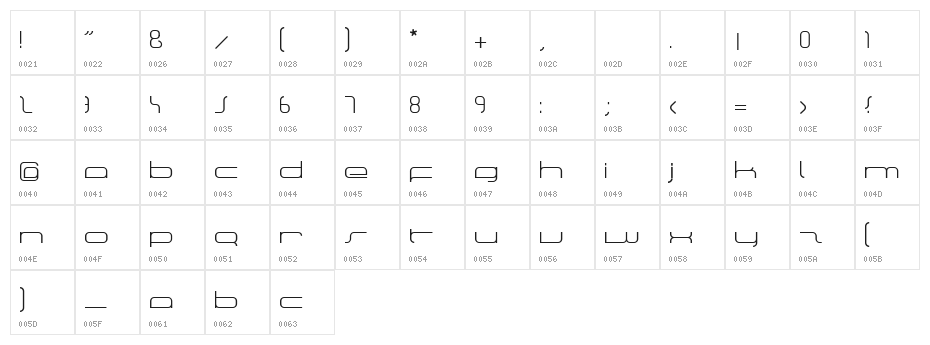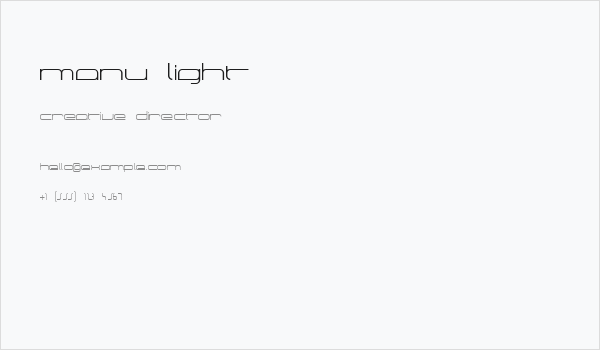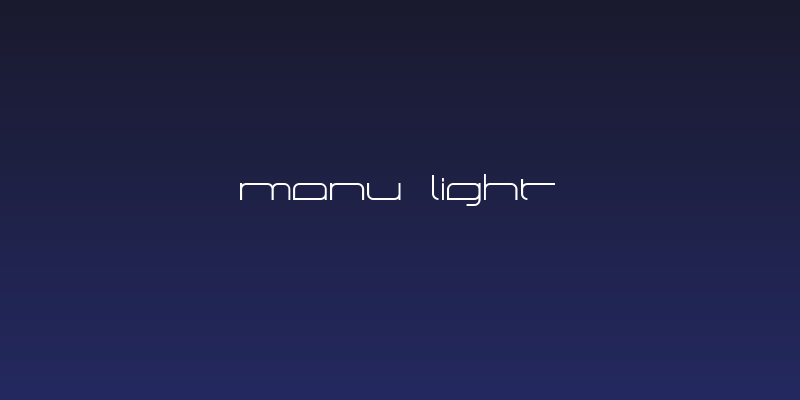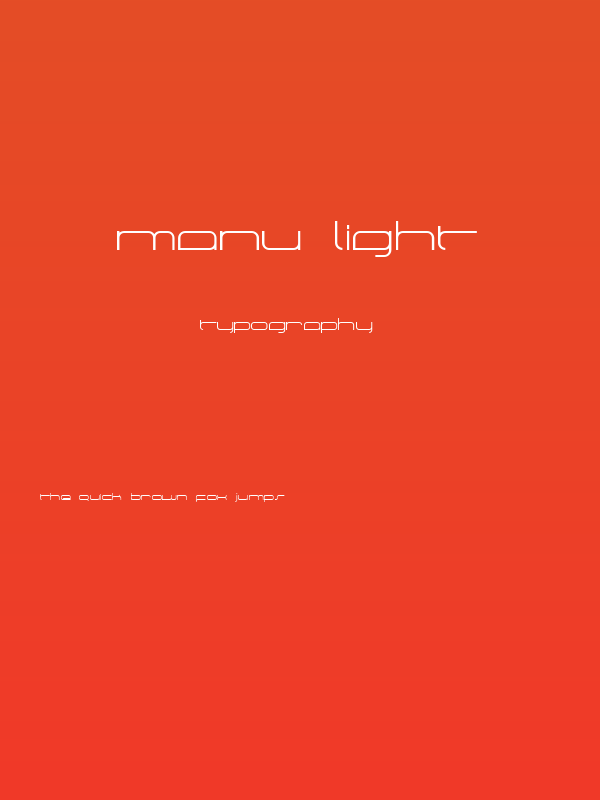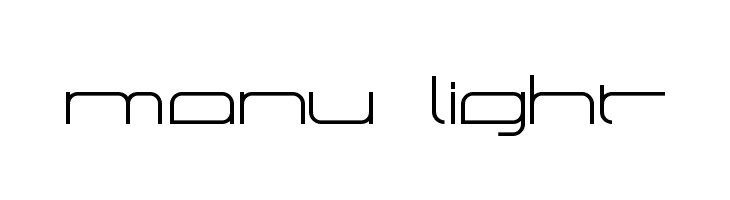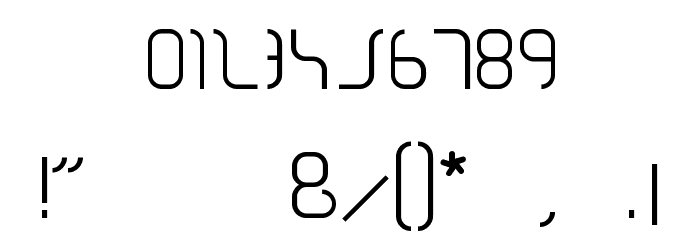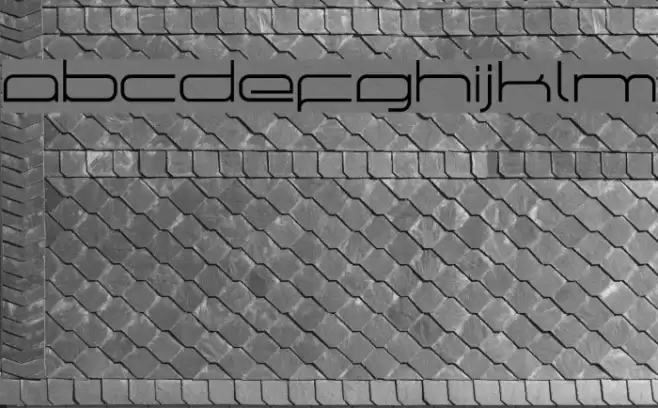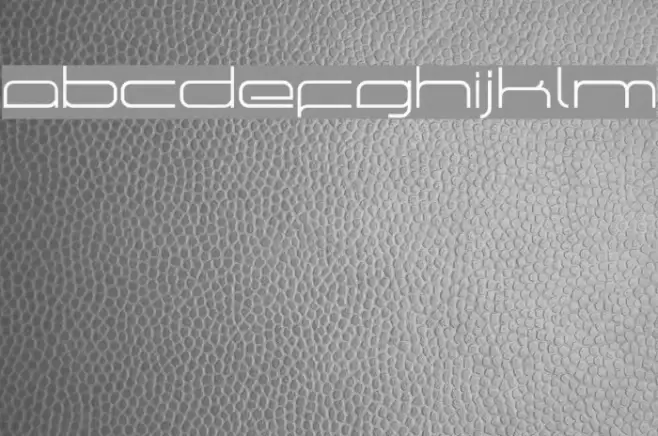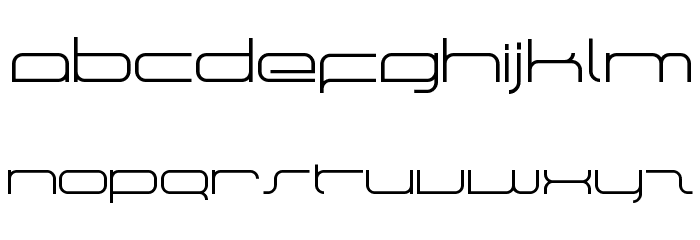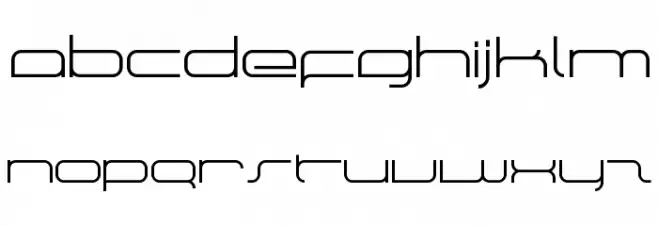
manu light Font
| Nume | manu light |
| Greutate | light |
| Proiecte propuse | Ideal for tech branding, modern web design, futuristic posters, and innovative product packaging. |